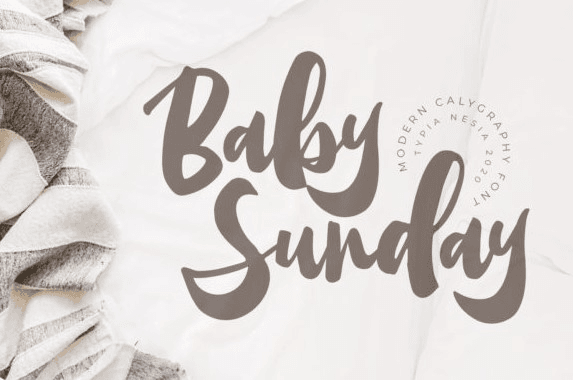
Baby Sunday Font
Baby Sunday - это великолепный и смелый рукописный шрифт, созданный для того, чтобы придать вашим заголовкам и логотипам стильный оттенок. Этот шрифт читается как сильный, уверенный и динамичный и может добавить тонны ностальгического характера в ваш дизайн.